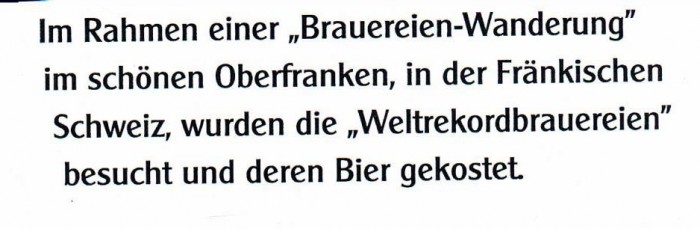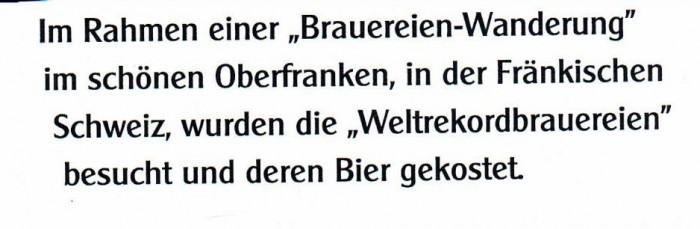
Schriftart gesucht
hat jemand eine Idee um welche Schriftart es sich bei diesem Text handeln könnte?
das sieht ganz grob nach einer Clearface Gothic aus:
Das große W scheint nicht zu passen? Die ClearGothic, ein Clearface Gothic Klon, von Softmaker passt auch nicht?
Die Schrift läuft auch etwas breiter und Identifont zeigt sich bei ähnlichen Schriften nicht besonders feinfühlig und gut informiert. Schade ... auf die Schnelle kann ich nicht weiter helfen.